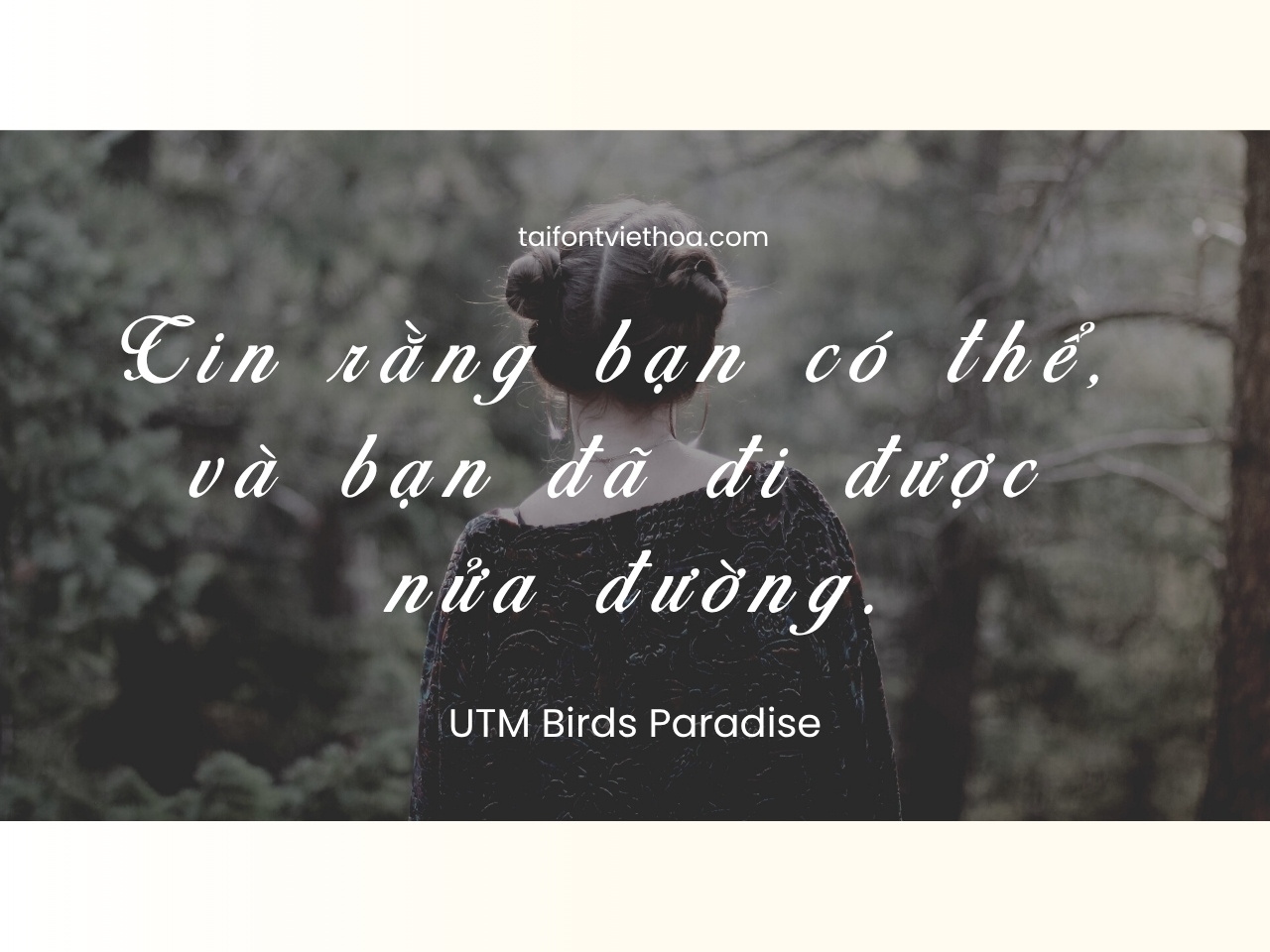
Font việt hóa UTM Birds Paradise
Giới thiệu về font UTM Birds Paradise
UTM Birds Paradise là một kiểu chữ script bay bổng, lấy cảm hứng từ những đường nét mềm mại và tự do của thiên nhiên – như tên gọi “Thiên đường của loài chim”. Font mang phong cách chữ viết tay nghệ thuật, thể hiện sự bay lượn uyển chuyển và đậm chất thơ. Phiên bản Việt hóa được thực hiện bởi Đinh Kiên, hỗ trợ đầy đủ tiếng Việt cùng hơn 100 ngôn ngữ khác sử dụng bảng mã Latin mở rộng. Font được taifontviethoa.com chọn lọc, thử nghiệm thực tế và ứng dụng trong nhiều dự án thiết kế cần tạo điểm nhấn cảm xúc và thẩm mỹ cao.
Đặc điểm thiết kế và ứng dụng của UTM Birds Paradise
Font sở hữu các nét chữ cong mềm, liên kết linh hoạt giữa các ký tự nhờ hệ thống ligature phong phú. Thiết kế chữ thanh mảnh nhưng đầy biểu cảm, tạo cảm giác lãng mạn, nghệ thuật và cá tính. UTM Birds Paradise phù hợp cho tiêu đề sáng tạo, thiệp cưới, logo thương hiệu cá nhân, trích dẫn truyền cảm hứng hoặc các sản phẩm cao cấp cần tính nhận diện nghệ